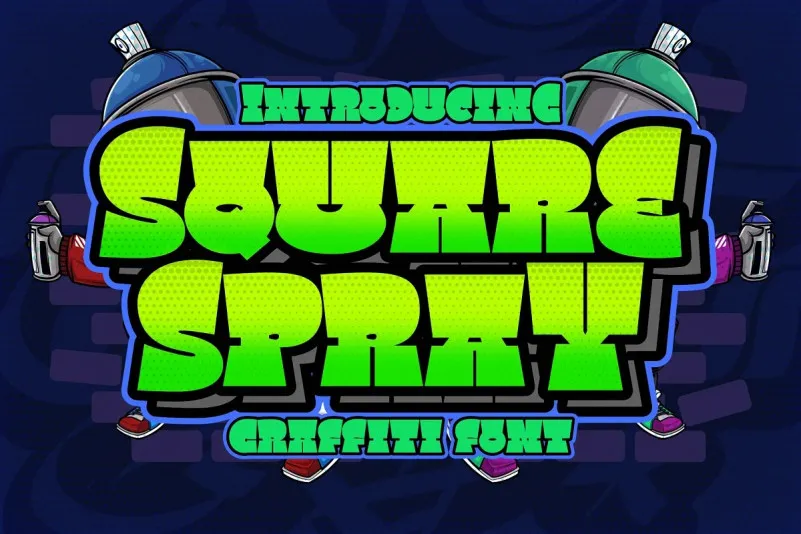
Square Spray Font – Fonte Grátis
Square Spray Font
A Square Spray Font é uma opção perfeita para quem busca adicionar um toque único à sua próxima arte digital ou design impresso. Inspirada no estilo graffiti, essa fonte Display oferece um ar despojado e divertido, ideal para aplicar em materiais como outdoors de música hip hop, posteres infantis, flyers educacionais e até mesmo capas de livros infantis, desenhos animados ou quadrinhos. Esta fonte foi projetada pela Blankids Studio, criativa parceira do 99designs, e tem um estilo que combina a simplicidade geométrica das formas quadradas com o espírito vibrante da arte graffiti. Seja para expressar temas de graffiti em suas criações ou criar uma identidade visual inspirada no universo da música hip hop infantil, Square Spray é certamente uma escolha inteligente. É a fonte perfeita para quem busca um estilo que se destaca e transmite energia.